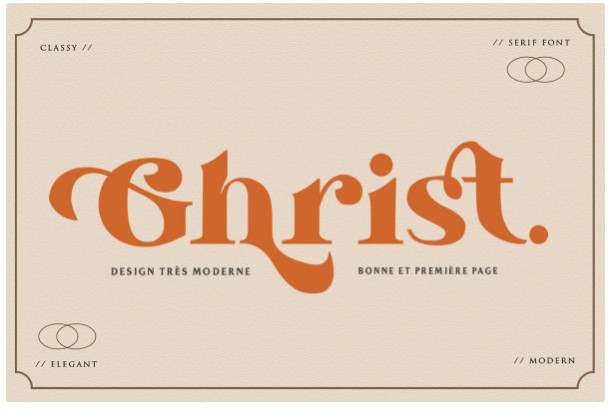
Creativemarket Ghrist Font 2021
[Creativemarket] Ghrist Font (2021)
Красивые и мягкие шрифты в современном стиле, которые могут придать вашим дизайнерским проектам современный, элегантный и роскошный вид. Шрифт содержит множество альтернативных символов, что облегчает выполнение различных дизайнерских проектов и доставляет удовольствие при наборе текста.
Вы можете использовать их для оформления постов в социальных сетях, логотипов, товаров, обложек книг, плакатов, миниатюр видеоконтента, цитат, целевых страниц, свадебных приглашений и многого другого, что вы можете сделать с помощью этого замечательного элемента для любого дизайна.